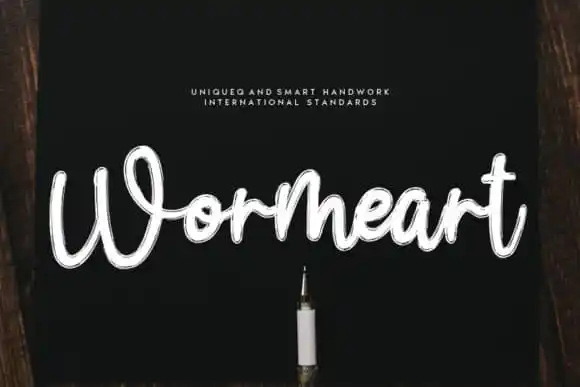
Wormeart Script Font – Download Grátis
A Wormeart Script Font é uma fonte escrita à mão que transmite sofisticação ao seu texto com influências clássicas do calligráfico, mantendo assim seu charme elegante. Ao mesmo tempo, se atualiza e ganha um toque fresco e contemporâneo que torna-a perfeita para qualquer projeto. Se apaixonar por ela é uma ótima maneira de levantar seu trabalho a outro nível. A Wormeart Script Font é uma opção perfeita para designers em busca de um toque único e sofisticado, capaz de dar vida à qualquer projeto visual.